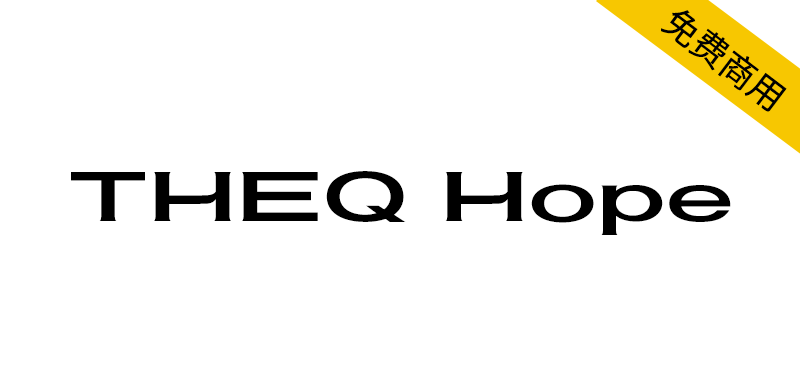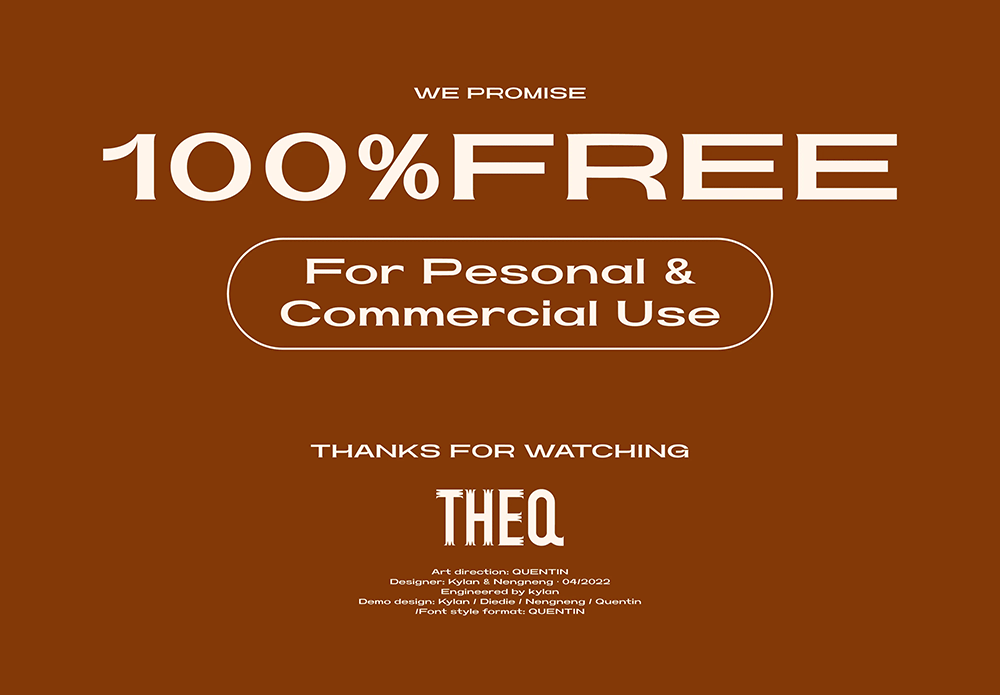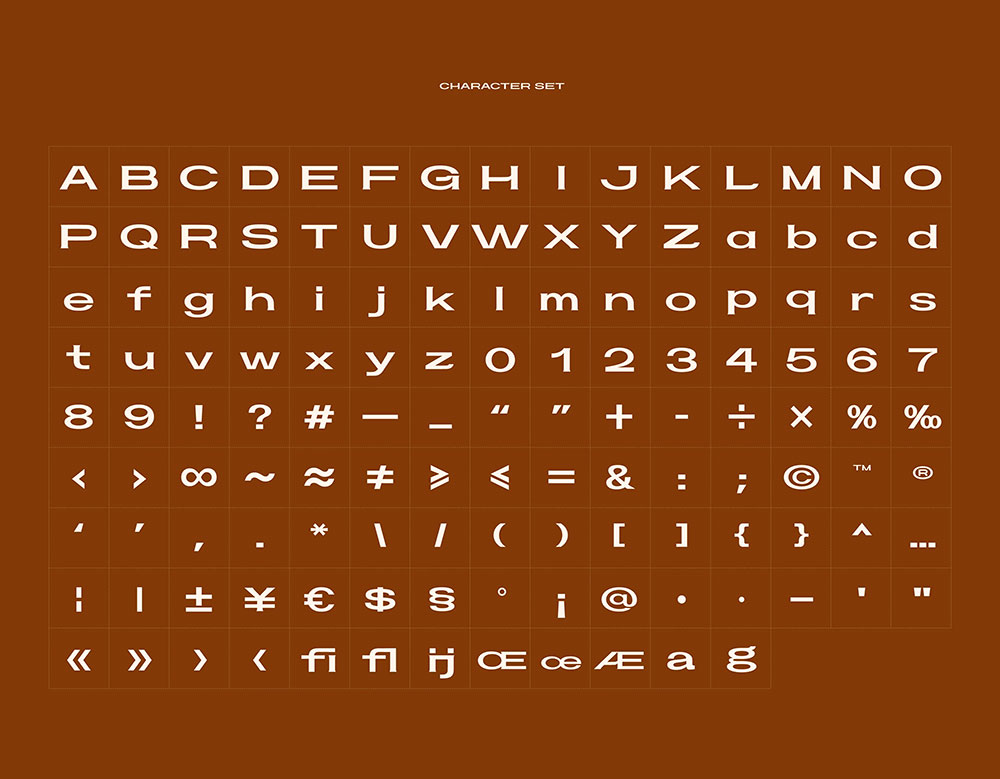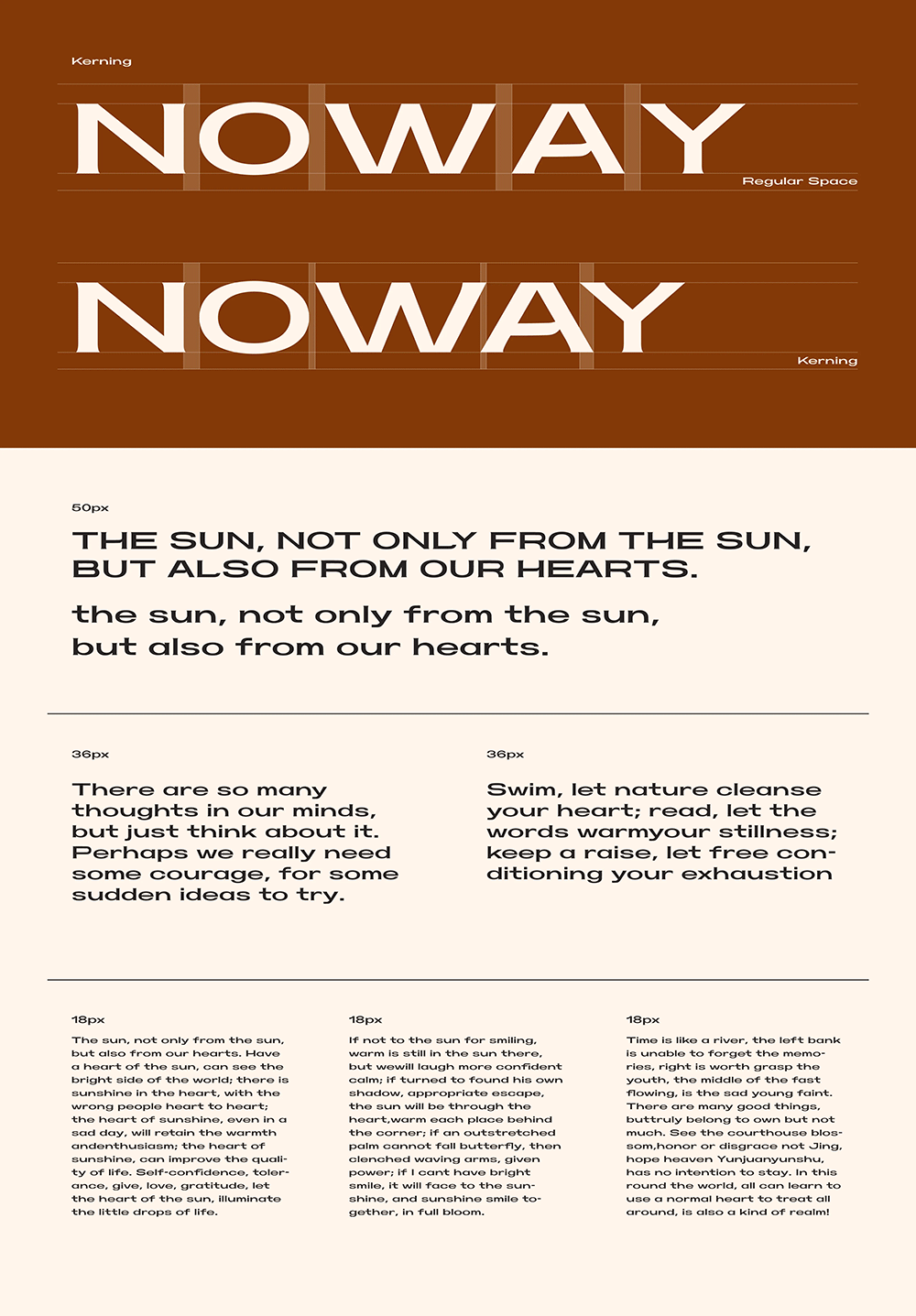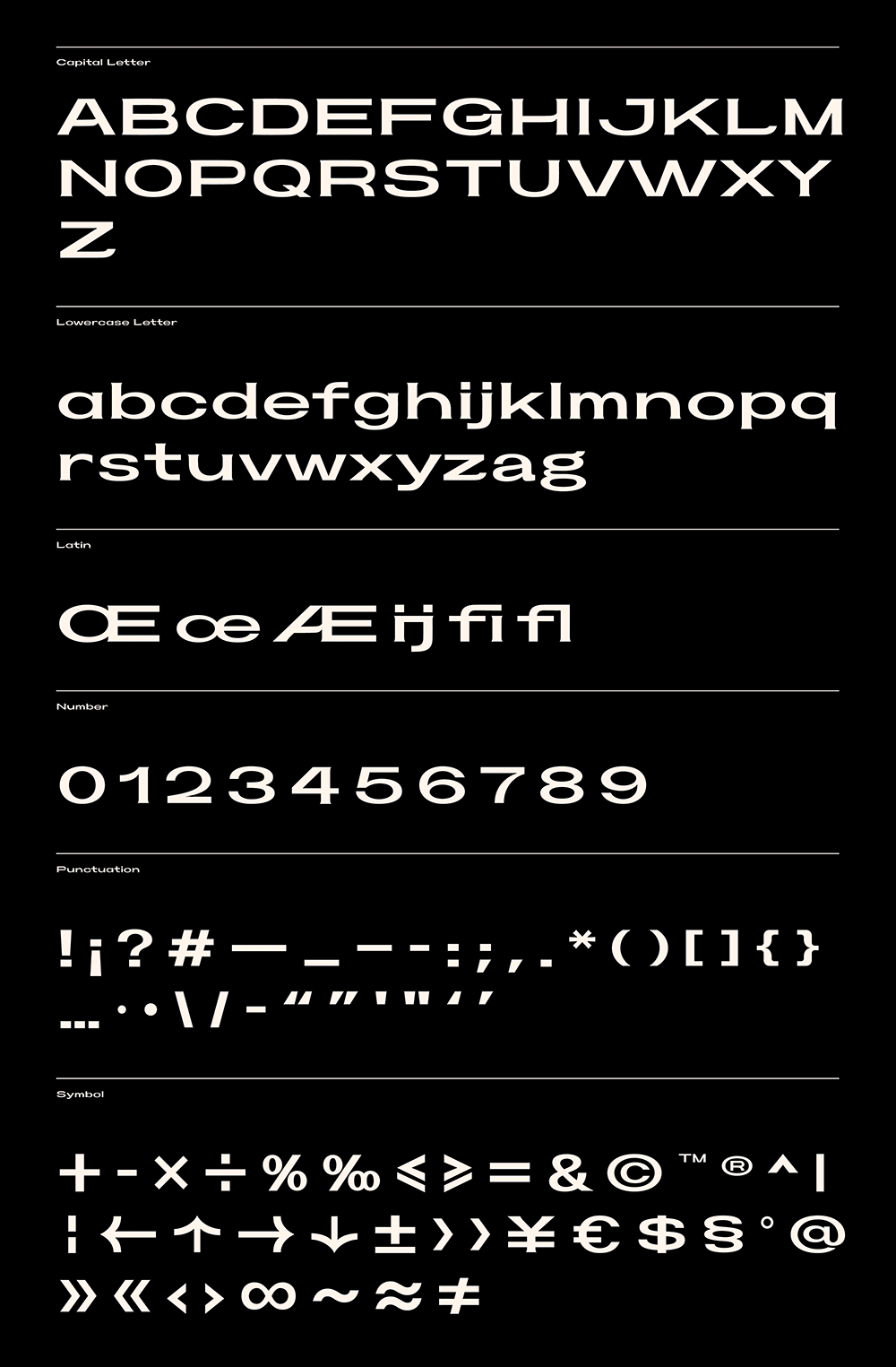
这款英文字体的名称为“Hope“,顾名思义就是希望的意思,我们希望无论在任何艰难的情况下都能够对未来保持信心,坚守理想与信念,苦难终究会过去,风雨后彩虹现,永远保持乐观积极向上的精神。
在字体方面,从一开始这款字体就是定位标题字体,经过我们的多轮测试,也的确更适合在标题中去使用,未来我们也会开发一些适应性更广泛的中英文字体,敬请期待吧~